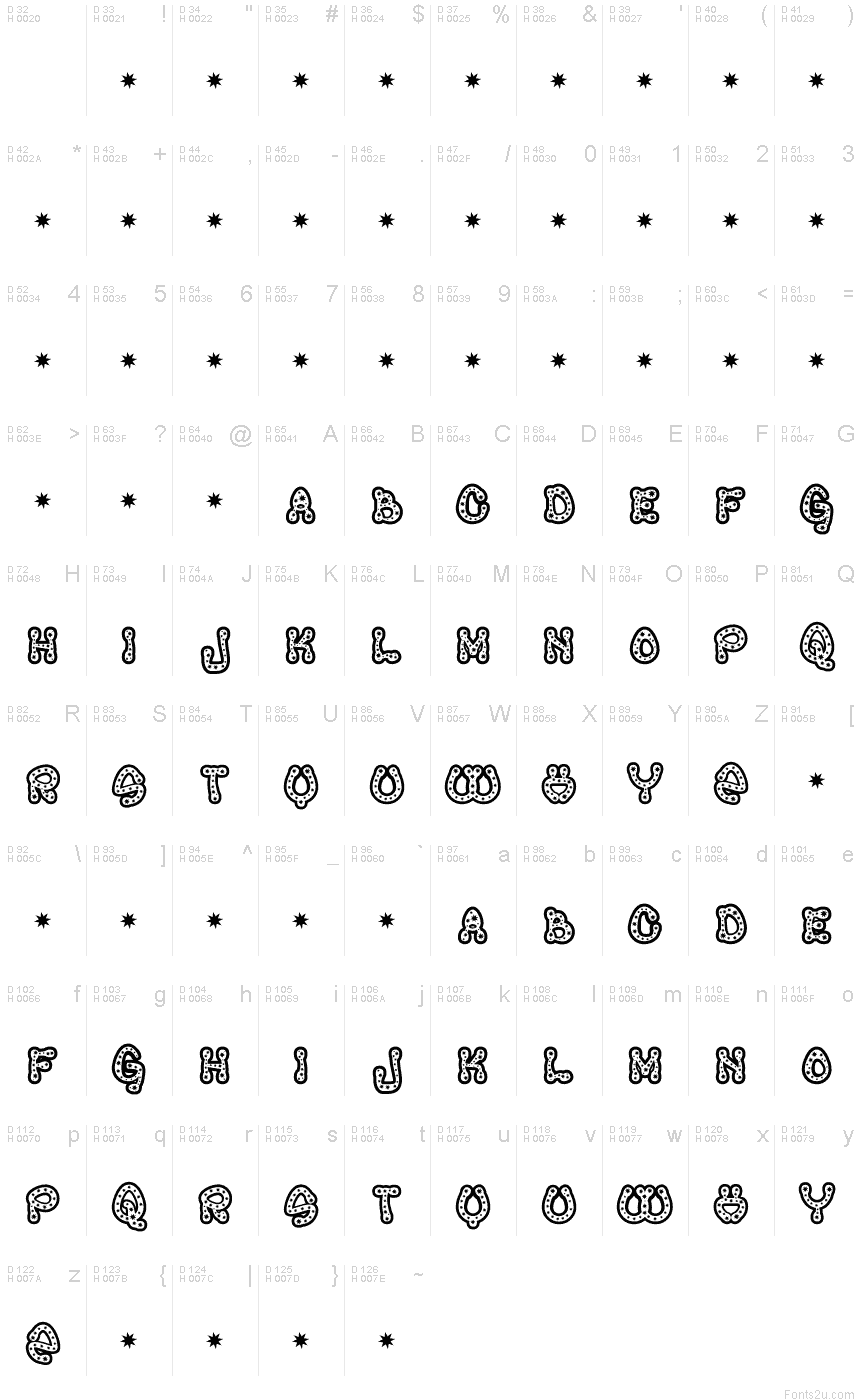
Rave Queen von Font-a-licious Fonts ist eine kostenlose, mit Sternen übersäte Bubble-Display-Schrift mit dem lauten Charme der späten 90er-Jahre. Die Buchstaben sind aufgebläht und abgerundet, mit einer dicken Kontur versehen und überall mit kleinen Sternen bestreut, was der Schrift eher einen verspielten Party-Poster-Look verleiht als ein elegantes oder poliertes Design.
Sie passt perfekt auf Club-Flyer, Grafiken für Kinderveranstaltungen, Sticker-Logos, Scrapbook-Überschriften und Cover-Texte, bei denen kurze Wörter das Muster und den Schwung optimal zur Geltung bringen. Als kostenlose Schrift aus dem Jahr 1998 eignet sie sich ideal für Titelkarten, Motto-Einladungen oder Merchandise-Designs, die nach klobigen Buchstaben mit integriertem kosmischen Konfetti-Effekt verlangen.